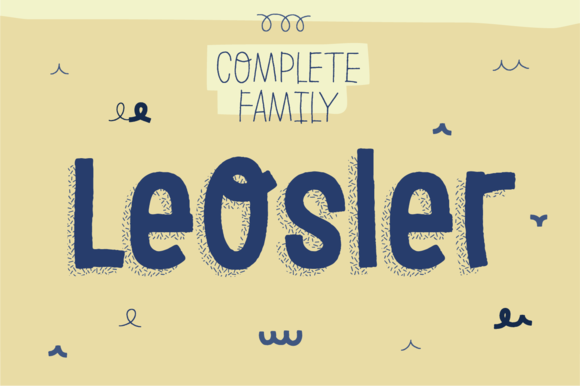
LeOsler Font Family – Download Grátis
LeOsler é uma família de fontes escrita a mão de Hamilton que adicionará um toque decorativo e divertido à sua identidade visual. Esta fonte inclui tanto a alfabeto latino quanto grego e cirílico, permitindo seu uso em diversas línguas como o inglês, espanhol, italiano, francês, alemão, polonês, checo, vietnamita, russo e grego, entre muitas outras. As características OpenType de LeOsler incluem ligaturas para caracteres repetidos tanto em letras maiúsculas quanto minúsculas, alternativas contextualizadas para todos os alfabetos suportados, quatro alternativas para o sinal da vírgula e figuras científicas, como superior e inferior. Essas características combinam-se para criar uma fonte única que é ideal para uso em materiais digitais e impressos, desde sites de blogs até livros impressos, garantindo que LeOsler seja tanto versátil quanto encantadora.